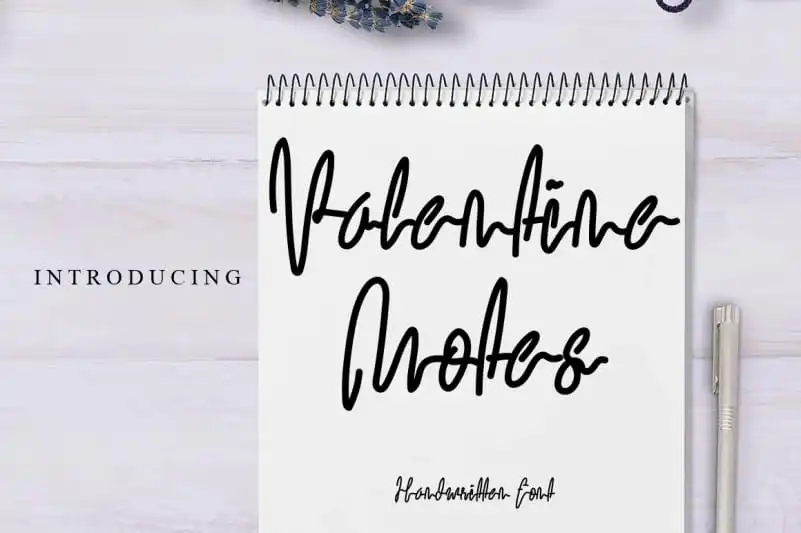
A Valentine Notes Script Font é uma elegante fonte escrita a mão que oferece um toque único e belo. Suas letras não são simplesmente bonitas; cada uma traz sua própria riqueza de detalhes, tornando-a perfeita para criar designs memoráveis. Perfeito tanto para marcas logos quanto para criações de marca e mensagens inspiradoras, a Valentine Notes Script Font é uma escolha ideal para aqueles que buscam algo autêntico e atrativo no design. Além disso, ela traz um toque romântico adequado para celebrar datas especiais. Com levincreative como seu designer, você pode garantir que sua mensagem seja ainda mais impactante e personalizada.